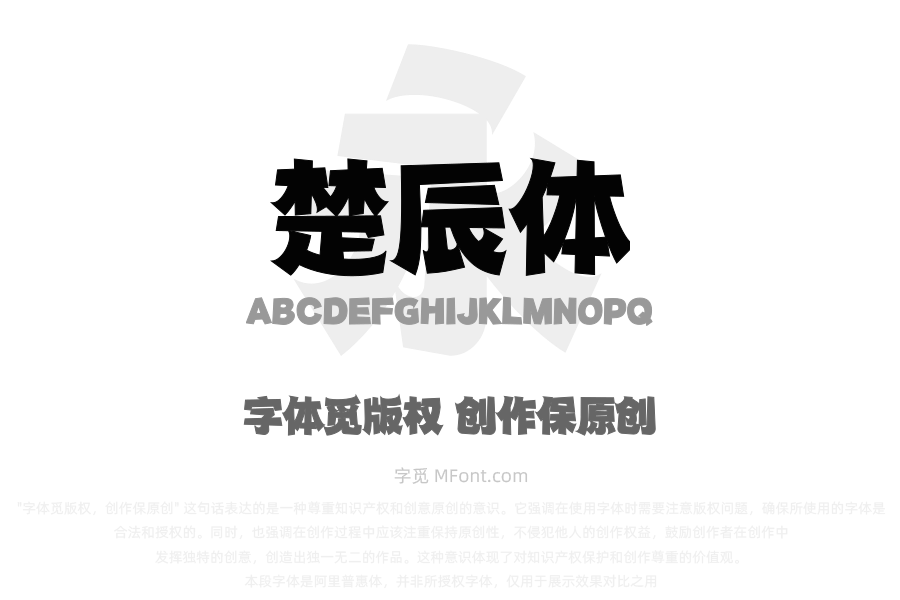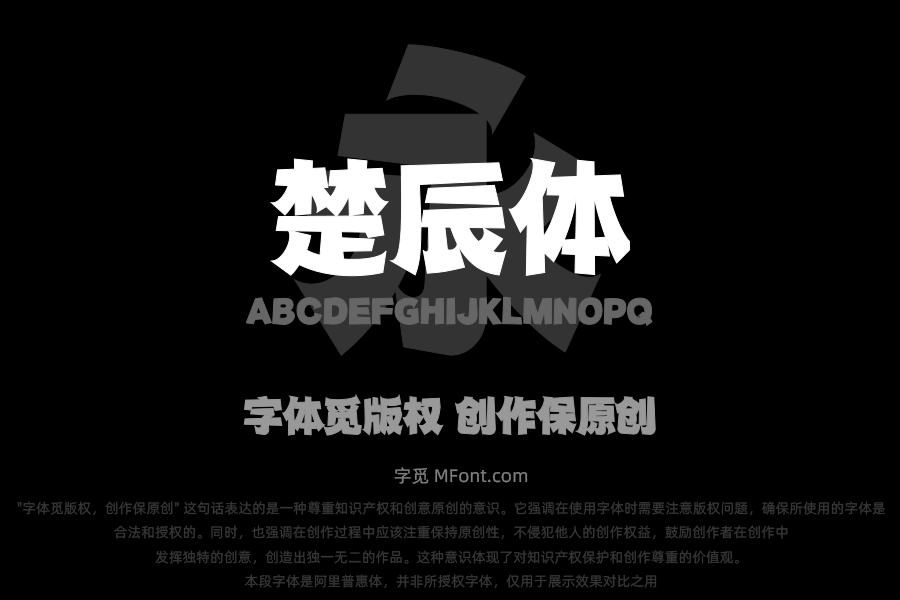
关于楚辰体字体字库信息
字体全名: 楚辰体
铸字厂: 丞言工作室
设计师: 陈艳艳
字体简介: 楚辰体是一款极具特色的字体,由丞言工作室出品。 其风格独具匠心,笔画细腻而富有张力,线条流畅且灵动多变。在字形设计上,楚辰体融合了古典与现代的元素,既展现出古朴典雅的气质,又不失时尚活力。每一个字符都仿佛蕴含着故事,散发着独特的艺术魅力。 这款字体由字觅网对外发售,适用于广泛的领域,无论是文艺作品的排版、品牌标识的设计,还是创意海报的制作等,都能为其赋予别样的视觉效果和情感表达。它以卓越的品质和独特的风格,在字体的海洋中脱颖而出。